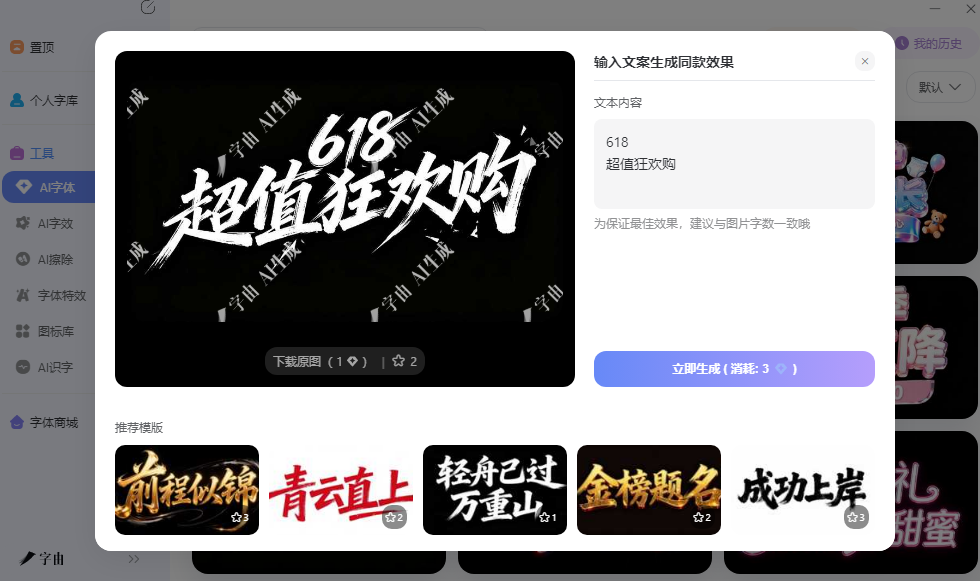
特殊字体下载资源推荐,小众字体一网打尽
常规黑体宋体用久了,做设计时总觉得缺一点辨识度。有些项目需要更特殊的视觉气质,比如恐怖片海报要用滴血质感的字体,复古收银小票需要点阵效果,程序代码展示需要等宽字符,或者做一张 Netflix 风格的标题图需要找到原版同款。这些需求在普通字体库里很难满足,得去专门搜集特殊字体下载渠道。这篇文章整理了几个小众平台,从 AI 生成特效到影视同款都有覆盖,帮你扩充常规字库之外的储备。
字由最近上线的 AI 字体功能,对需要特殊字体下载的人来说是个省时的路子。打开客户端左侧导航栏的工具入口,进入 AI 字体页面,能看到一个模板库,目前提供了 400 多种特效模板,其中专门有一大类是书法风和国潮风,还有霓虹灯、金属感、液态效果、破碎玻璃等偏视觉冲击力强的风格。
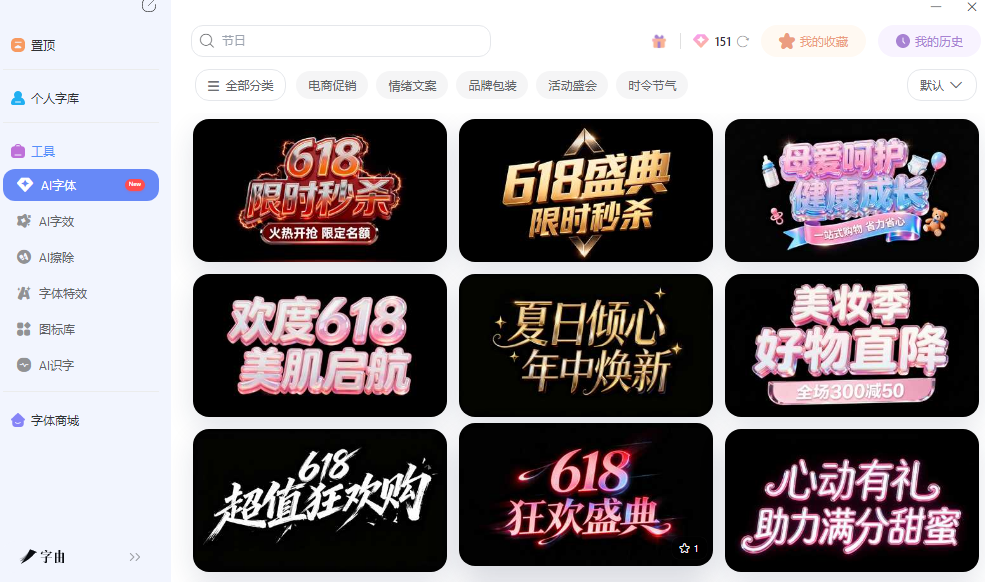
操作流程就三步。第一步在左侧筛选栏里点对应风格标签,比如国潮风或者特效字,所有相关模板会一次性列出来。模板预览图里会展示效果,有的偏水墨晕染,有的偏鎏金质感,有的像碑刻拓印,有的像霓虹发光。鼠标滑过一个模板,预览图里会立刻用你预设的文字展示效果,不用点进去就能看到大概。第二步点做同款,在右侧输入框里填你的文案,注意最好和模板原本的字数保持一致,字数不一致排版可能会歪。第三步点立即生成,等待几秒后系统就会输出设计好的字体图片,生成后可以下载透明背景的 PNG 格式,直接拖进 PS、剪映或者海报里就能用。
除了 AI 字体,字由的 AI 字效功能也值得一提。它提供一键生成字体特效的能力,在客户端内选择霓虹灯、金属感、手写体等模板,输入文字,几秒内就能获得效果惊艳、可直接下载使用的图片。这个功能和 AI 字体互补,AI 字体偏向整体风格渲染,AI 字效偏向局部特效叠加,两者结合可以做出更复杂的视觉标题。对于需要频繁产出社交媒体配图、电商 Banner 或者活动海报的设计师来说,这两个工具把复杂的特效制作简化成了几次点击。
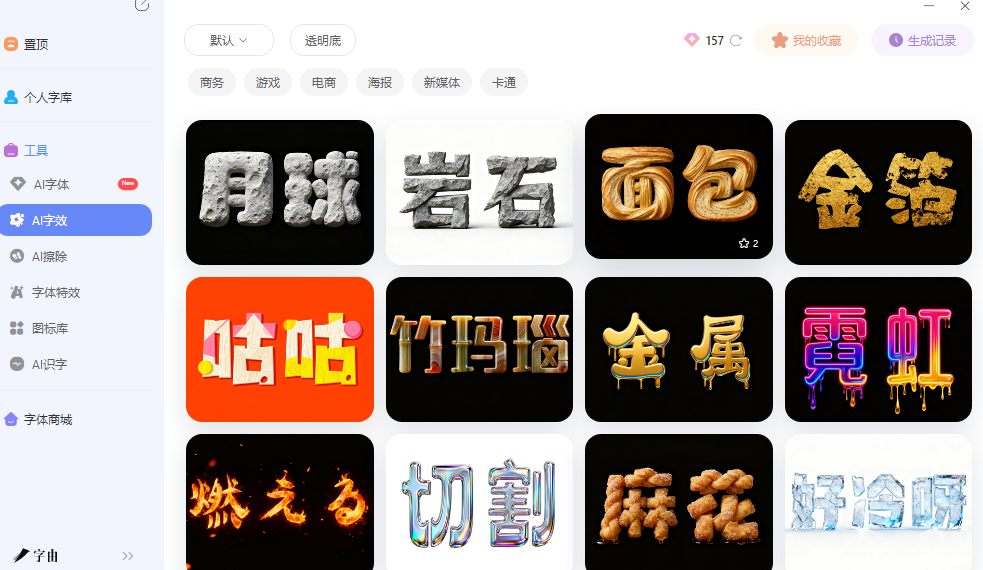
2、DeeFont
DeeFont 是一个分类很细的特殊字体下载平台,首页展示了 Commercial Fonts、Handwriting Fonts、Cute Fonts、Halloween Fonts 等主题合集。往下翻能看到更详细的分类体系,包括 Gothic、Handwritten、Script、Display、Slab Serif、Serif、Sans Serif 等风格标签,还有按字母排序和按外语分类的导航。
这个平台的特色是节日和场景化分类比较全。除了常见的 Halloween 恐怖字体,还有 Valentine、Easter、Christmas 等节日专题,以及 Greek、Japanese、Chinese、Arabic、Mexican、Roman、Russian 等外语字体。对于需要特定文化氛围字体的项目来说,这种按地域和节日分类的方式很直接,不用在无关结果里翻找。每款字体都展示了清晰的预览图和授权说明,部分支持免费商用,下载前可以确认。DeeFont 的界面设计比较活泼,浏览体验轻松,适合想要快速找到主题化字体资源的用户
3、colorany
这个平台专注收录特殊字符和等宽字体,目前整理了 29 款免费特殊字符字体。首页展示的 Courier New、Lucida Console、Consolas 等字体,都是程序员和代码编辑器里常见的系统等宽字体。每款字体都支持在线调整字号、字重、样式、文字装饰和颜色,实时看到效果后再决定是否下载。
等宽字体在普通设计项目里不常用,但在特定场景下很难替代。比如做复古科技风格海报,需要模拟终端显示器效果;做编程教程封面,需要展示代码片段;做收银小票或者复古打印效果,需要点阵或者等宽字符。这个平台的字体全部标注为完全免费商用,不需要额外授权,下载后可以直接安装使用。对于需要技术感、复古感或者模拟特定设备显示效果的特殊字体下载需求,这个平台的资源比较精准
4、Fontesk
Fontesk 是一个按基础字形分类的免费字体平台,导航包括 All Fonts、Sans Serif、Serif、Slab Serif、Script、Display、Handwritten。筛选区域提供了 Free for Commercial Use、Free for Personal Use、OFL 等授权选项,勾选后可以快速过滤出符合需求的字体。
平台的字体预览图比较直观,每款字体都展示了不同应用场景的效果图,方便判断是否符合项目需求。对于需要特定风格特殊字体下载的设计师来说,按类型分类的浏览方式很高效,可以直接定位到 Display 或者 Handwritten 分类,找到风格化的艺术字体。Fontesk 的更新频率比较稳定,经常会有新的免费商用字体加入,定期浏览可以发现一些新资源。下载流程顺畅,字体文件格式通用,安装后在 Photoshop、Illustrator 等设计软件里可以直接调用。
5、Font Meme
Font Meme 是一个专注流行文化字体的特殊字体下载平台,首页展示了 Remarkably Bright Creatures、Beef、Heated Rivalry、The Unforgettable Fire、Summer House、They Will Kill You 等电影和电视剧的标题字体。除了影视字体,平台还提供了 Social Media Fonts 和 Free Calligraphy Fonts 等分类。
这个平台的特色是收录了大量知名作品使用的原版字体,对于需要做致敬海报、影视同人设计或者模仿特定风格的项目来说,能找到最接近原版的资源。平台还提供了在线文字图形生成器,输入文字后可以选择不同字体和效果,直接生成图片下载。这种在线生成的方式适合不需要安装字体、只需要一张效果图的场景。Font Meme 的资源覆盖电影、电视剧、音乐、游戏等多个领域,浏览起来有点像逛影视周边,随机发现惊喜的概率比较高。
做海报或者影视物料需要快速出特殊风格字体,字由的 AI 字体和 AI 字效生成透明背景 PNG 图片,配合每日免费算力,从生成到使用的流程比较轻量。其余四款工具的共同点是均聚焦于单一下载或展示功能,无法提供 AI 生成和跨软件即时调用能力,且输出的结果多为安装文件或静态图片,适用场景相对有限。可以按具体需求来选择适合自己的特殊字体下载网站。